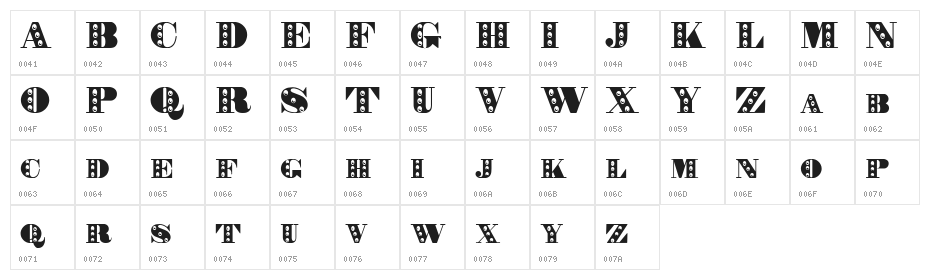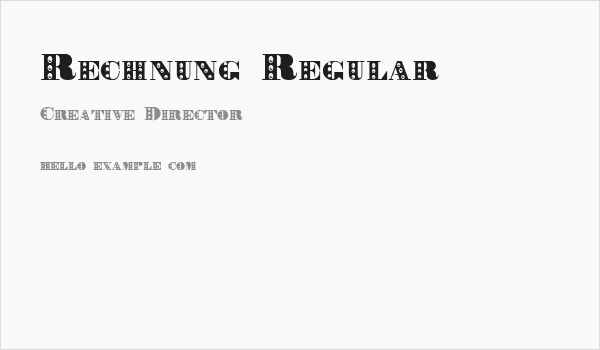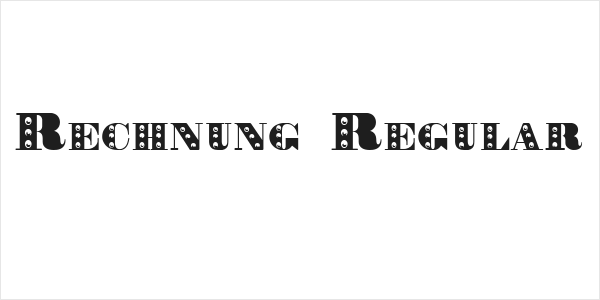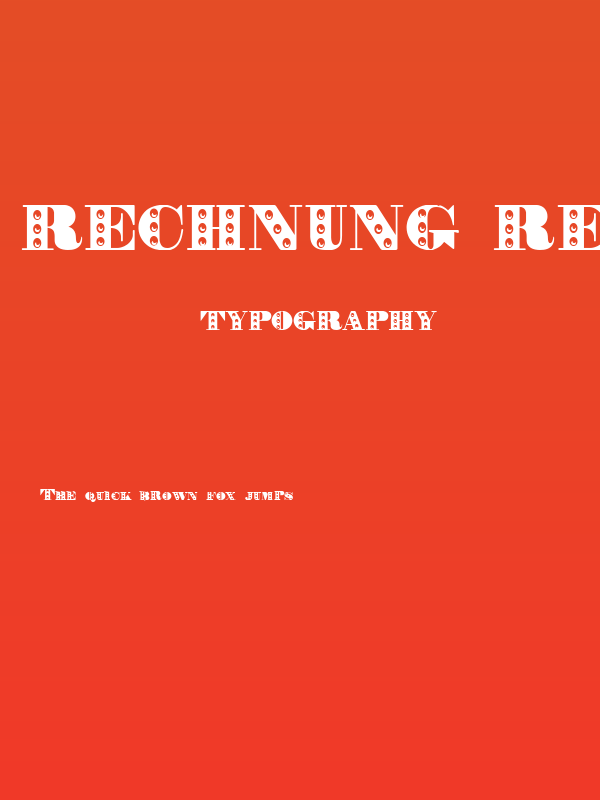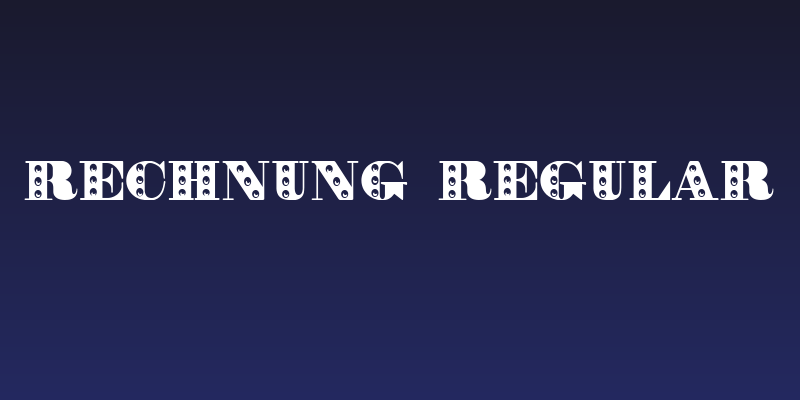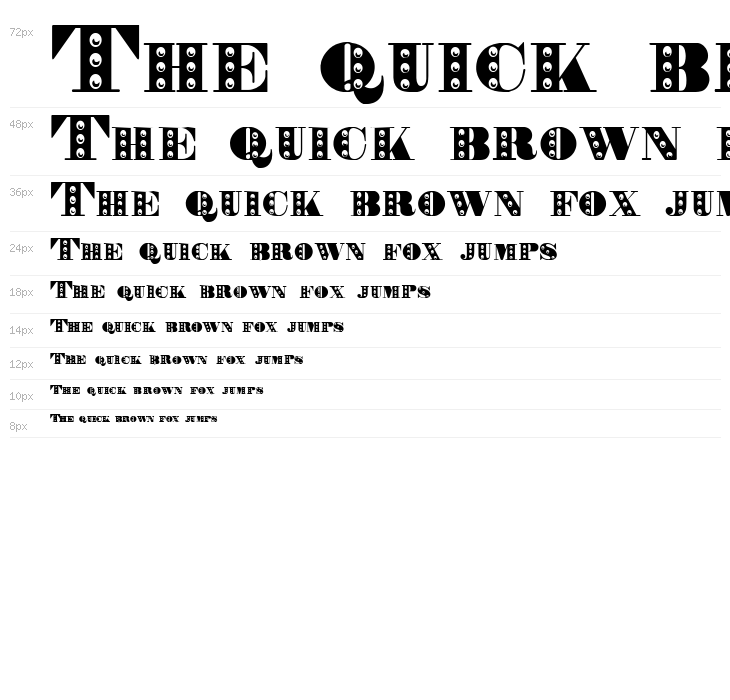
Rechnung Regular Font
| Gesamtstil | Vintage |
| Vorgeschlagene Projekte | Perfect for vintage-themed posters, theatrical event flyers, or any project needing a playful, eye-catching typeface. |